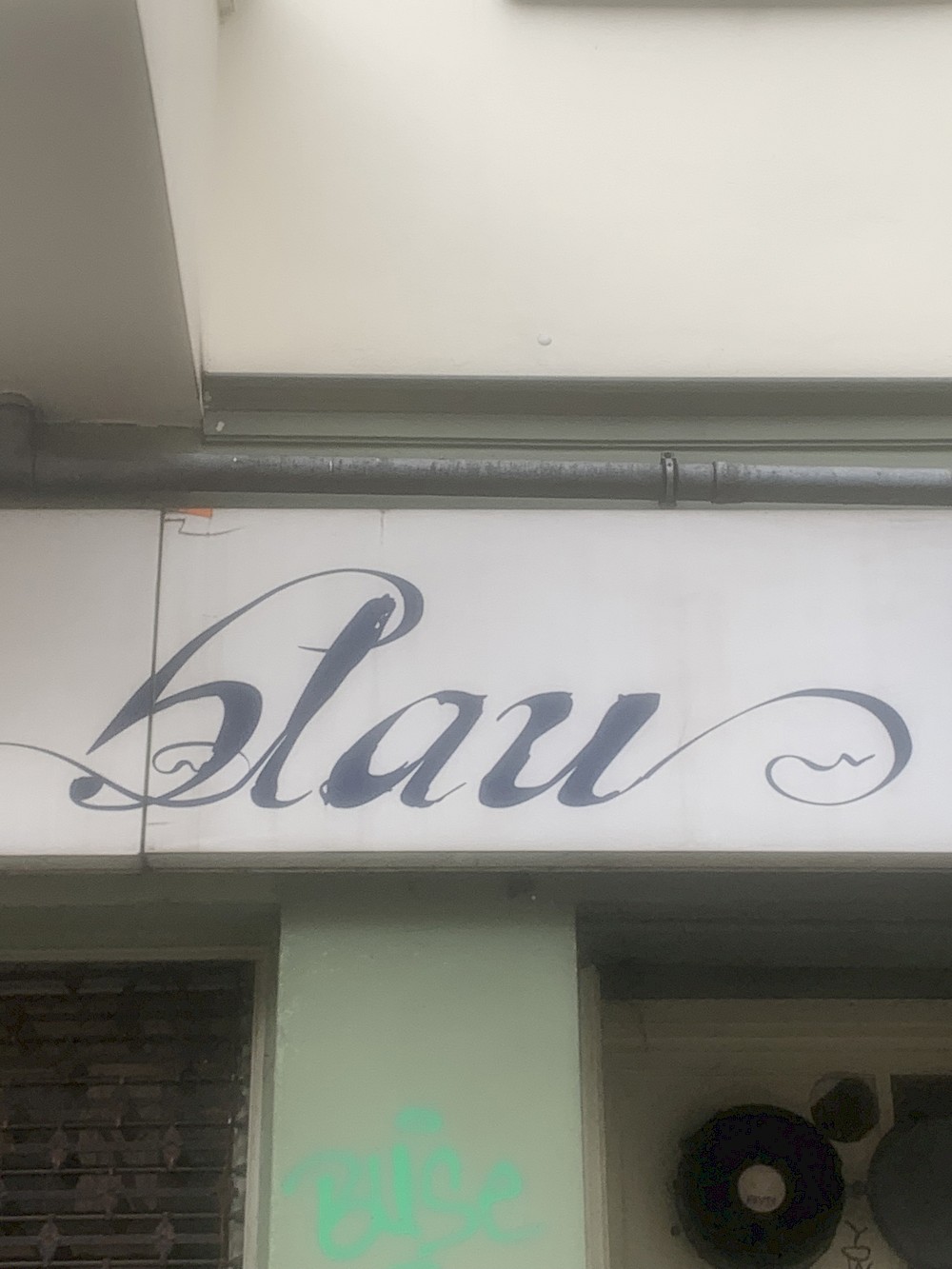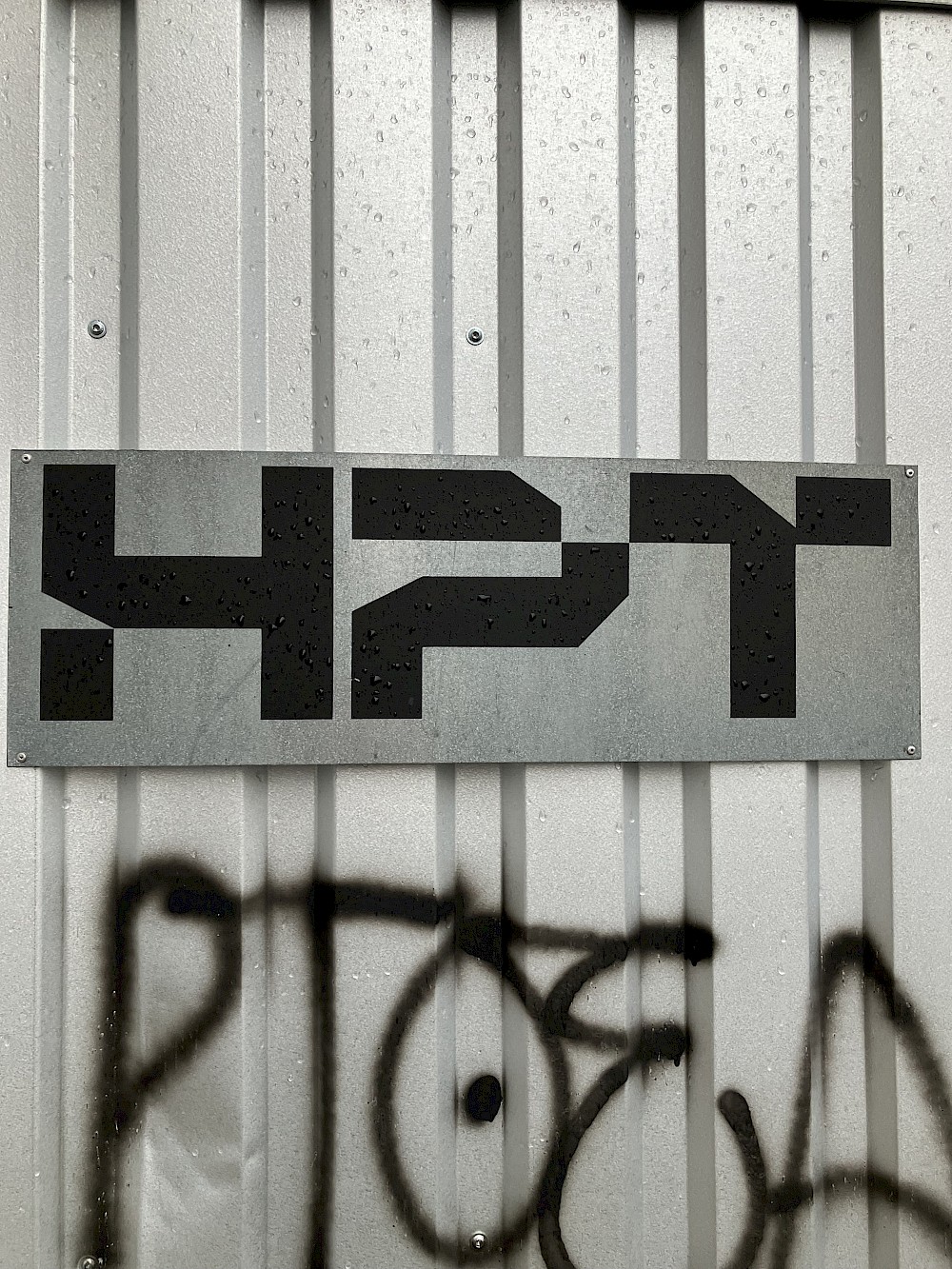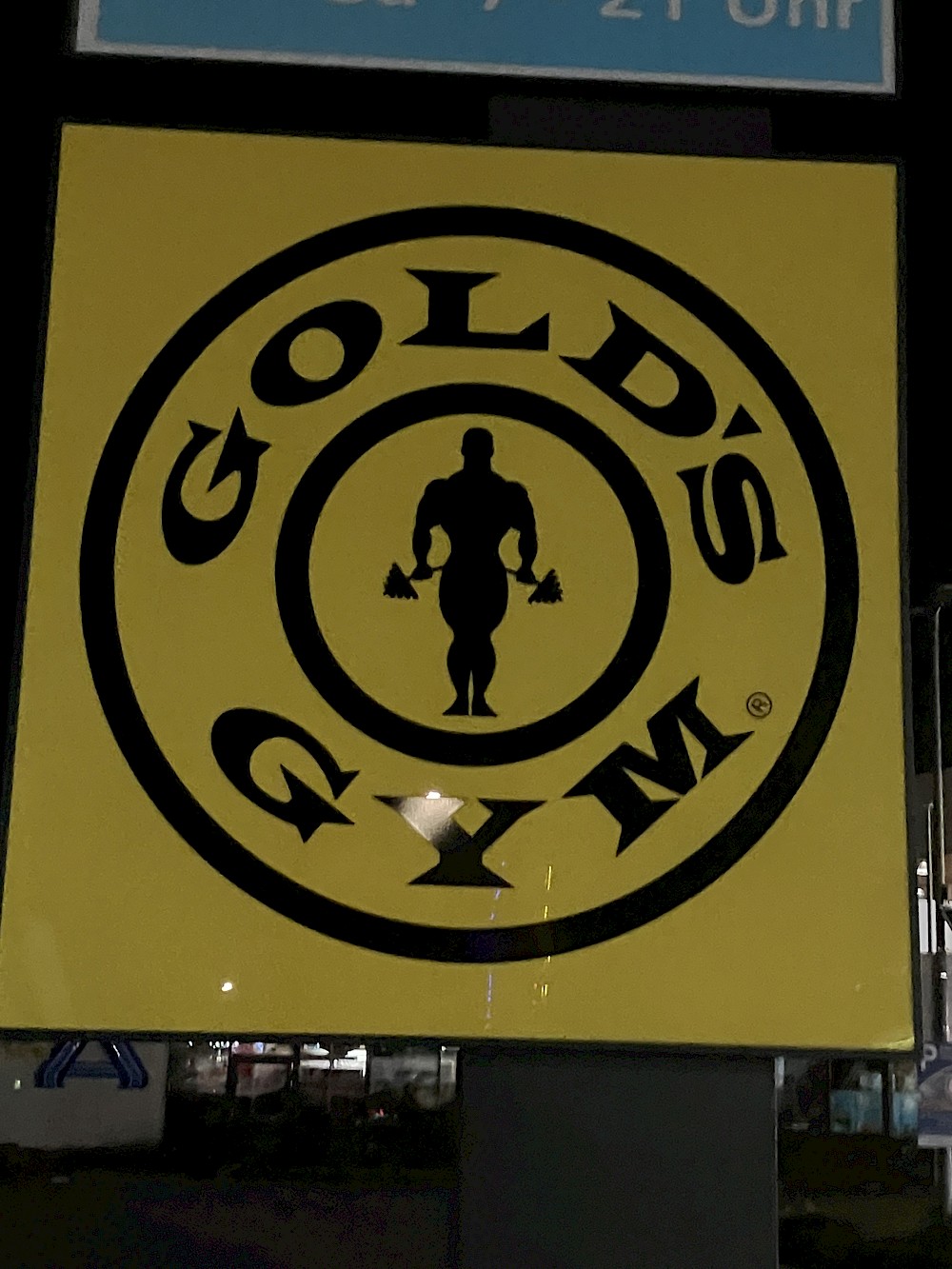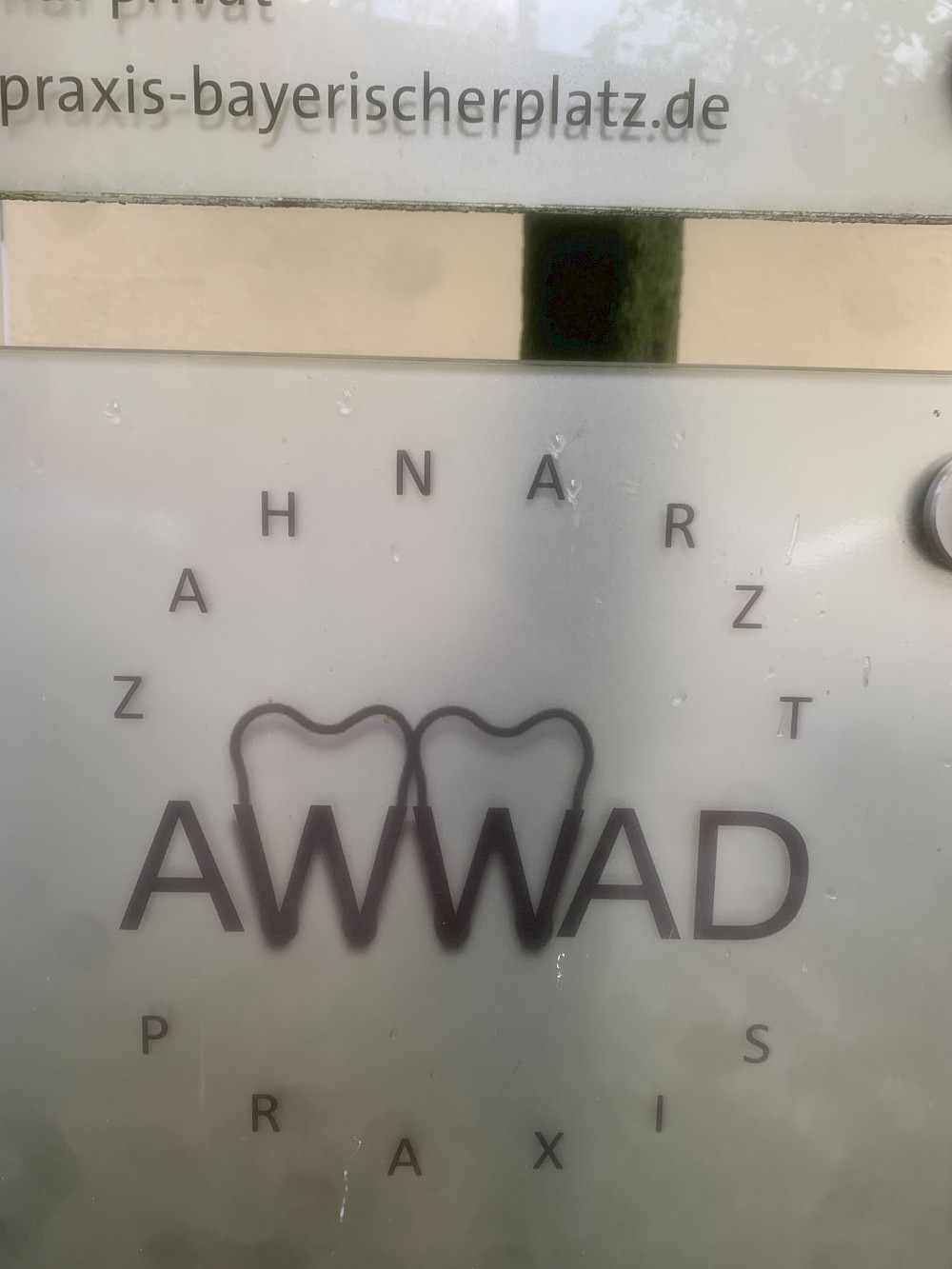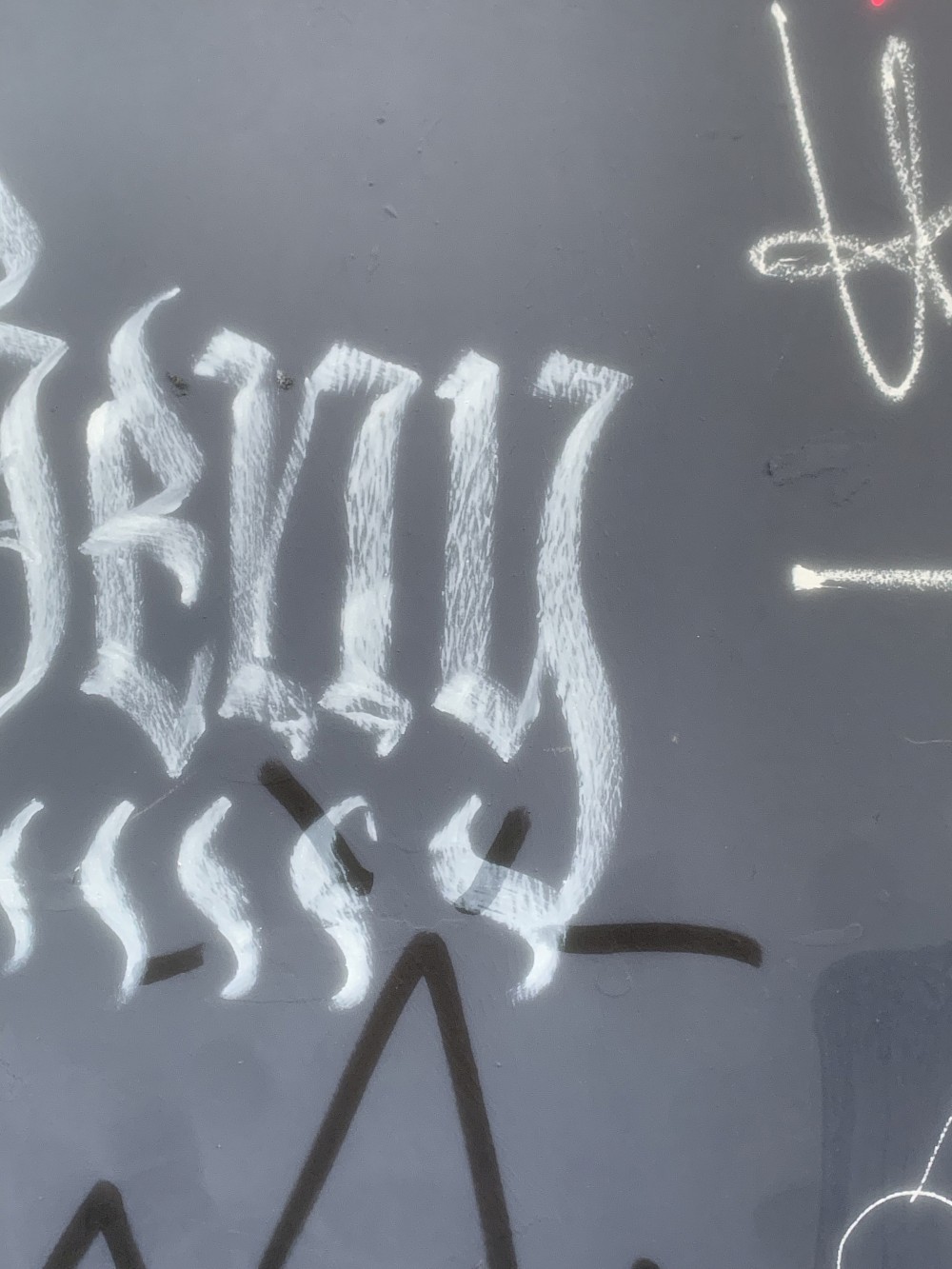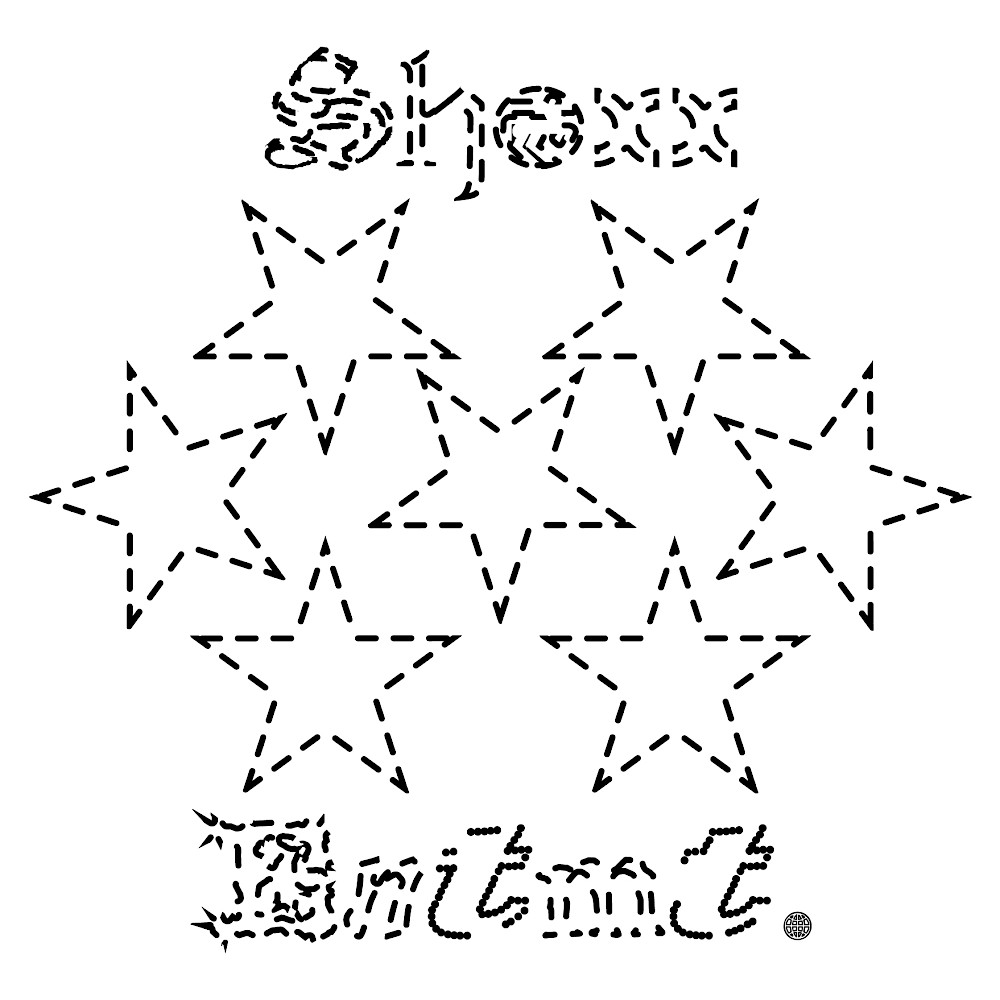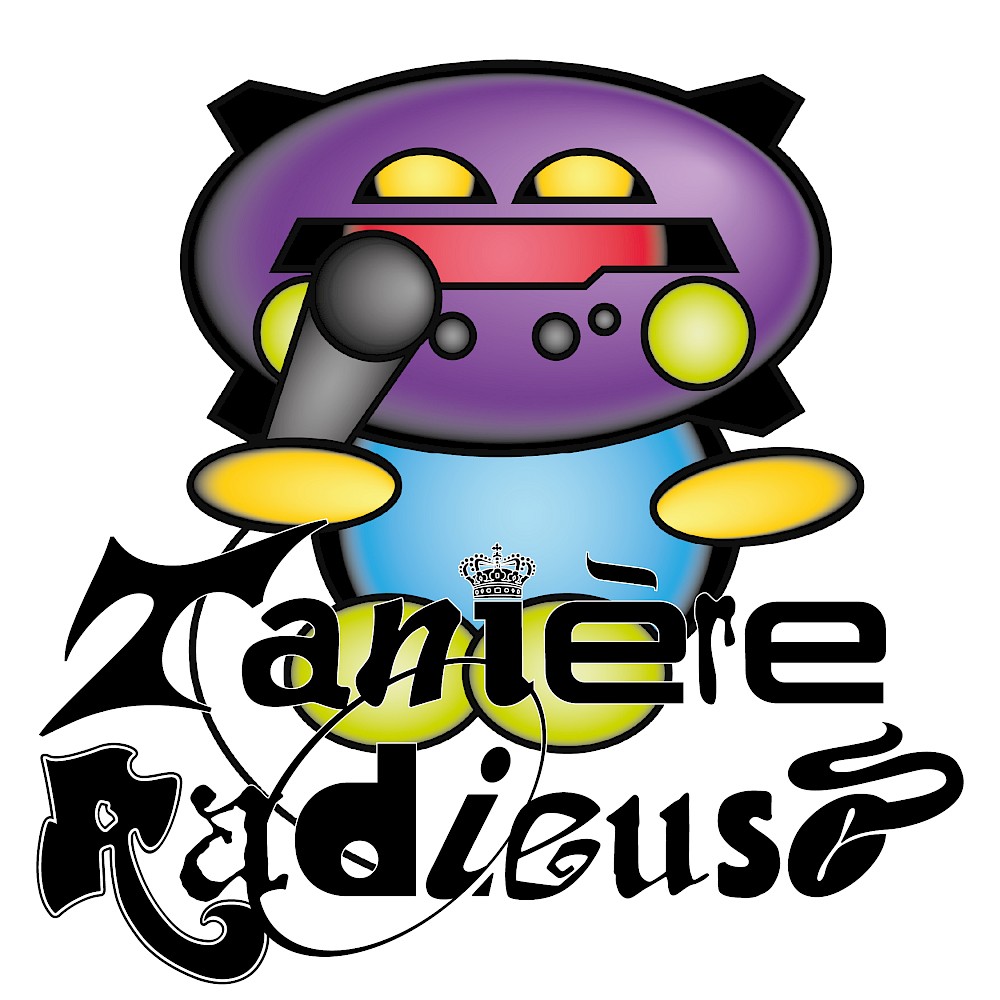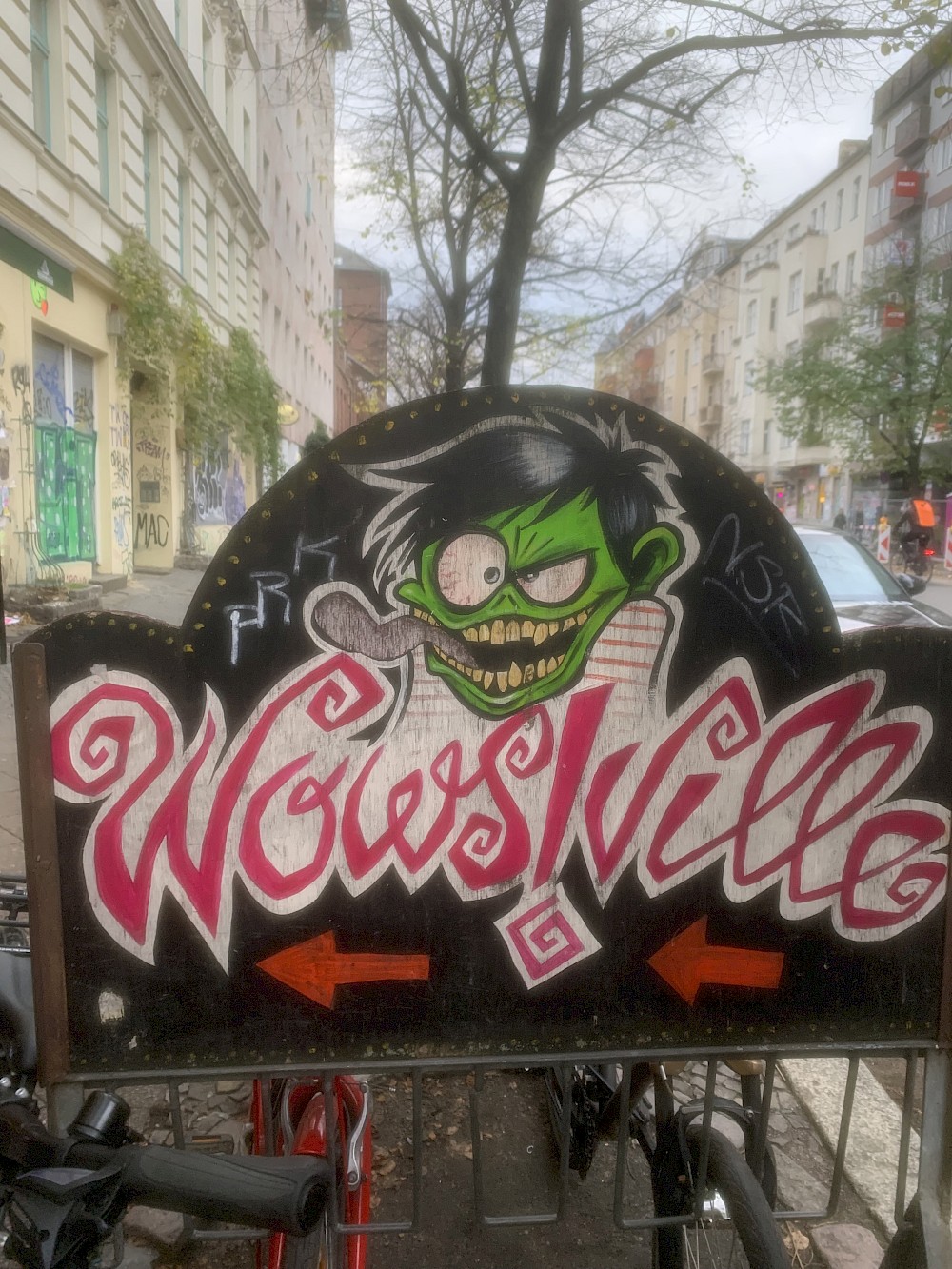
‼️ pour cette typo l'idée ça serait que chaque personne qui parte en Allemagne et qui trouve une lettre rigolote et qu'iel aimerait voir figurer dans l'alphabet, l'envoie dans ce feed de discussion pour que collectivement on la redessine ‼️
petites photos de la provenance des différentes lettres qu'on retrouve dans la typo. Certaines sont pas des lettres mais des logos que j'ai utilisé comme des lettres hehe (cf: le I de Mr. Muscle)
Hello! je reviens d'un séjour à Cologne où j'ai vu ce lettrage! il serait trop cool à ajouter
Hiver 2023, je pars en Interrail en Allemagne avec mes deux meilleur·es ami·es: Jeanne et Ismaël. Au cours de ces deux mois de voyage, avec Ismaël, on a l'idée de créer une typographie vernaculaire en collectant des lettres toutes issues de sources variées : devantures, logos, tags, livres, etc. Au-delà du caractère drôle et random des lettres sélectionnées, l'objectif était d'archiver et de redessiner des caractères qui, pour la plupart, auront disparu dans les années à venir. ( ◡̀_◡́)ᕤ
Finsternis